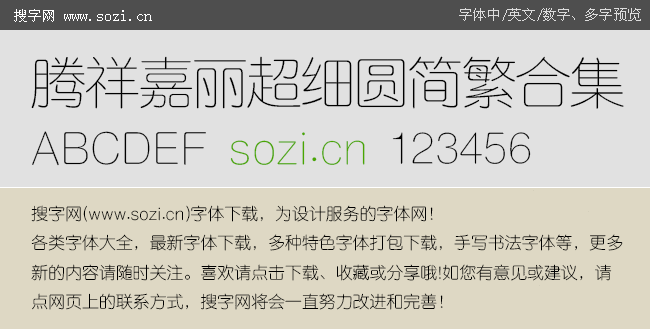
騰祥嘉麗超細(xì)圓簡(jiǎn)繁合集
搜字網(wǎng)提供一款騰祥嘉麗超細(xì)圓簡(jiǎn)繁合集中文藝術(shù)字體下載,騰祥嘉麗超細(xì)圓是一款應(yīng)用于設(shè)計(jì)方面的簡(jiǎn)體中文漢字,該字體線條纖細(xì)精致,字形大方得體,整體效果出眾,并且字庫(kù)完整,可用于藝術(shù)設(shè)計(jì)、包裝印刷、簽名設(shè)計(jì)、圖形設(shè)計(jì)等領(lǐng)域。